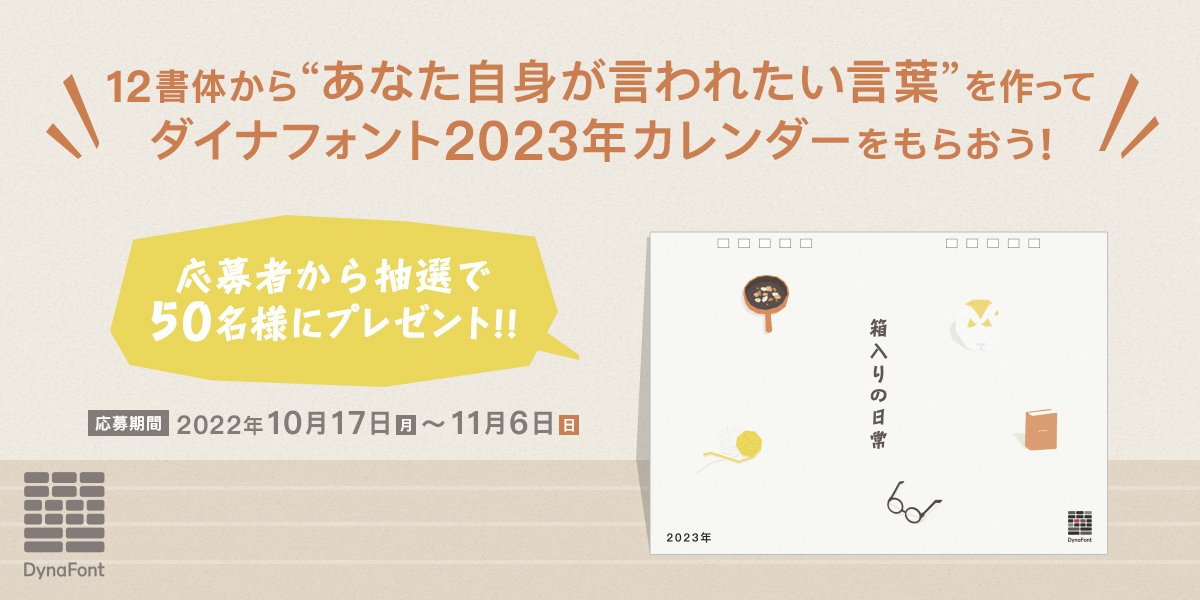
ダイナフォント2023年カレンダーが当たる『12書体から “あなた自身が言われたい言葉” を作って「ダイナフォント2023年カレンダー」をもらおう!』が2022年11月6日まで開催
ダイナコムウェアは、激動の時代に文字が生きるチカラになることを信じて、“あなた自身が言われたい言葉”を、2022年10月17日(月)~11月6日(日)までの期間に募集。また、参加者の中から抽選で50名に、ダイナフォント12書体を使用したポエムによる2023年カレンダー「箱入りの日常」をプレゼントする。
ダイナフォント2023年カレンダー「箱入りの日常」
ダイナフォント2023年カレンダー「箱入りの日常」は、日常という箱を開けると見えてくる、かわいらしいイラストと言葉の面白みを伝えるダイナフォント12書体を使用したポエムによるカレンダー。
通常の卓上カレンダーより少し大きいA5サイズで、機能面も考慮に入れて記入スペースの確保や当月の前後1ヶ月、六曜も表記しているほか、読み心地を追求したダイナコムウェアフラッグシップフォント「金剛黒体」をベースに作成しており、毎日の生活の中で快適に使用できる。
激動の時代に文字がチカラになる!“あなた自身が言われたい言葉”
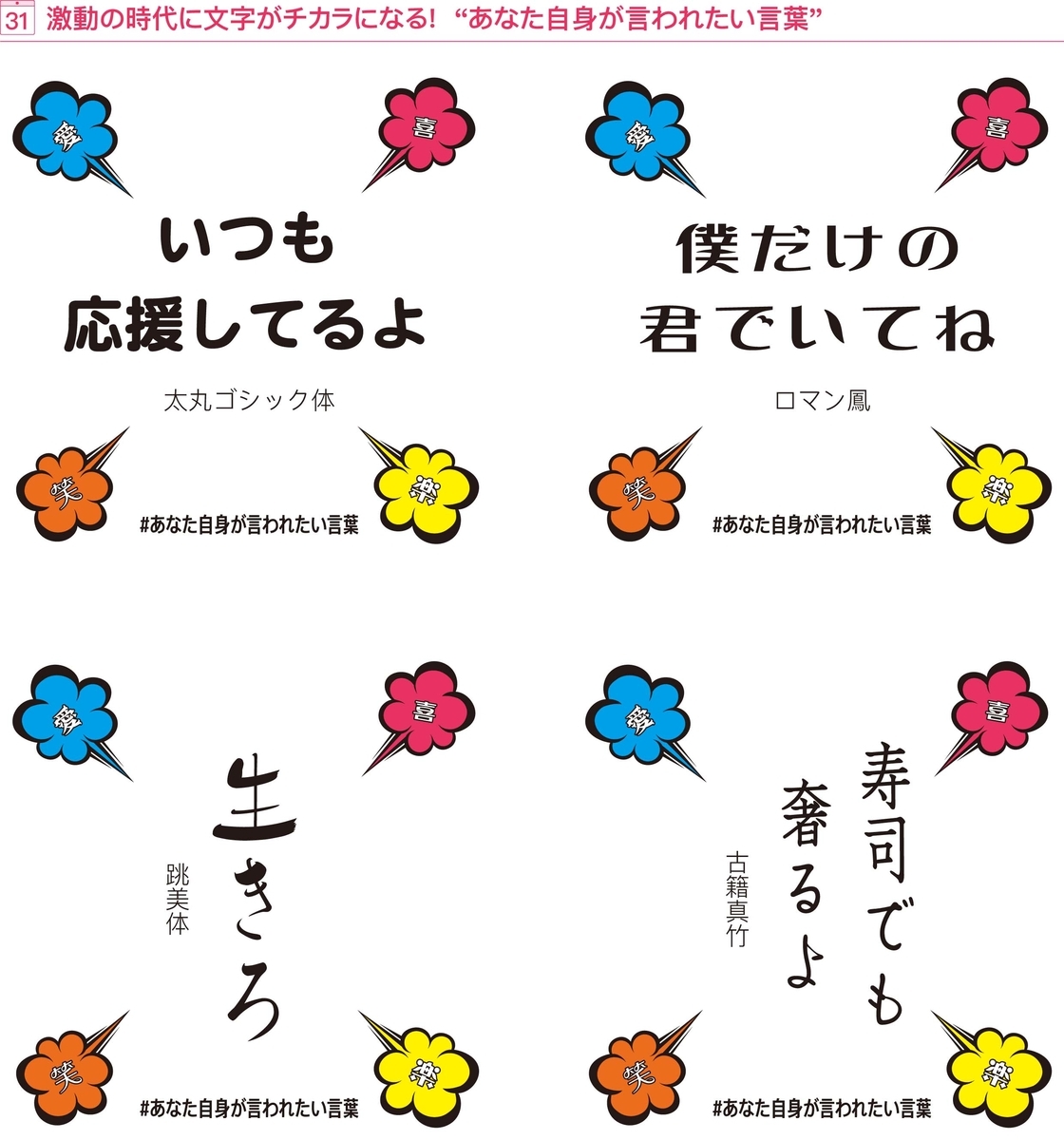
ダイナコムウェアでは、文字が暗い気持ちを吹き飛ばすチカラになることを信じて、“あなた自身が言われたい言葉” を募集。
家族や恋人、友人、同僚、推しのアイドルや俳優、ミュージシャン、スポーツ選手、YouTuber、はたまたマンガやアニメの登場人物などなど、大切な人や憧れの人、大好きなキャラクターから『こんな言葉を言ってもらえたら元気が出るだろうなぁ』と空想しながら、ダイナフォント2023年カレンダー「箱入りの日常」でも使用している表情豊かなダイナフォント12書体から1書体選んで、言ってもらえたら嬉しい、元気が出る言葉を作ろう。